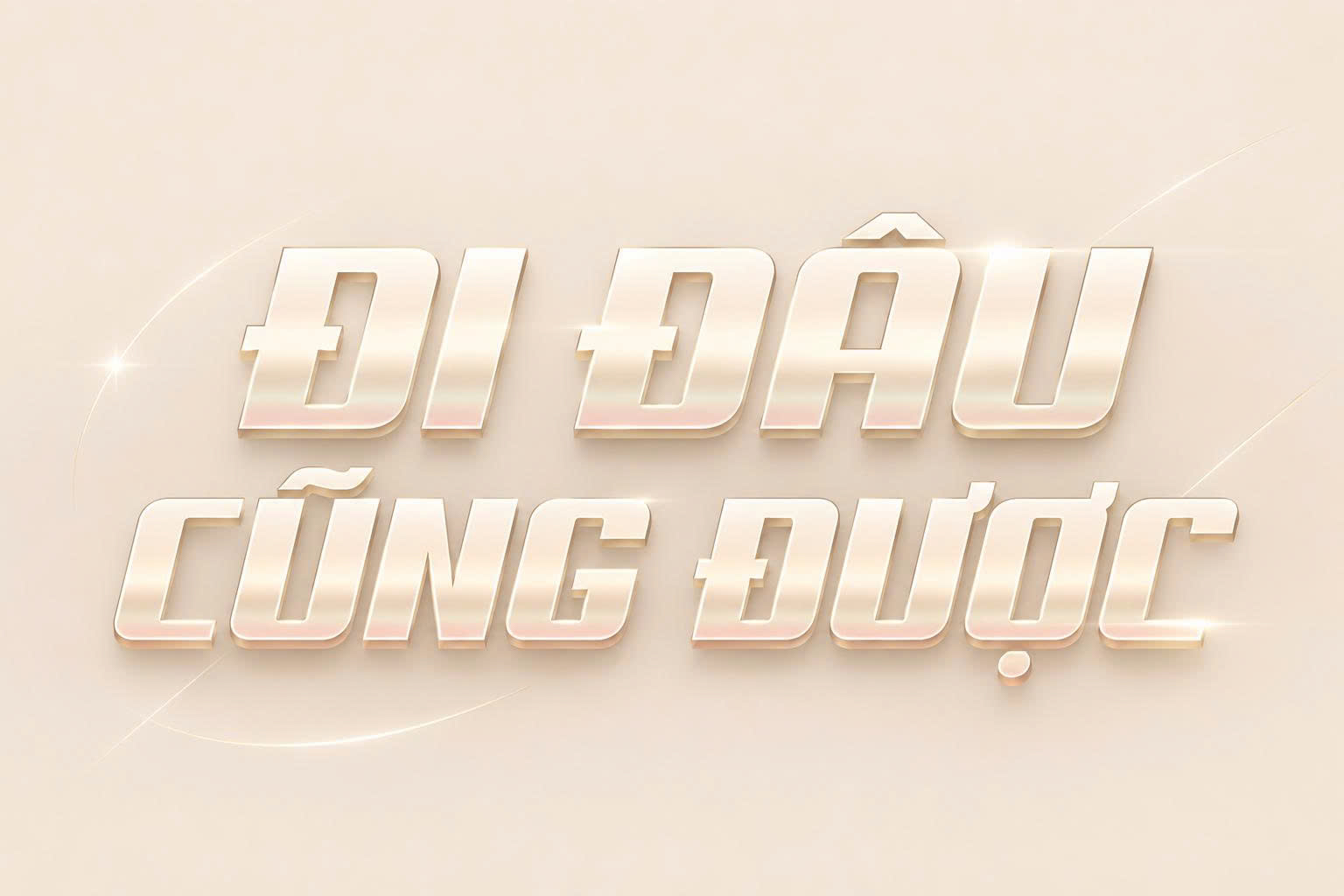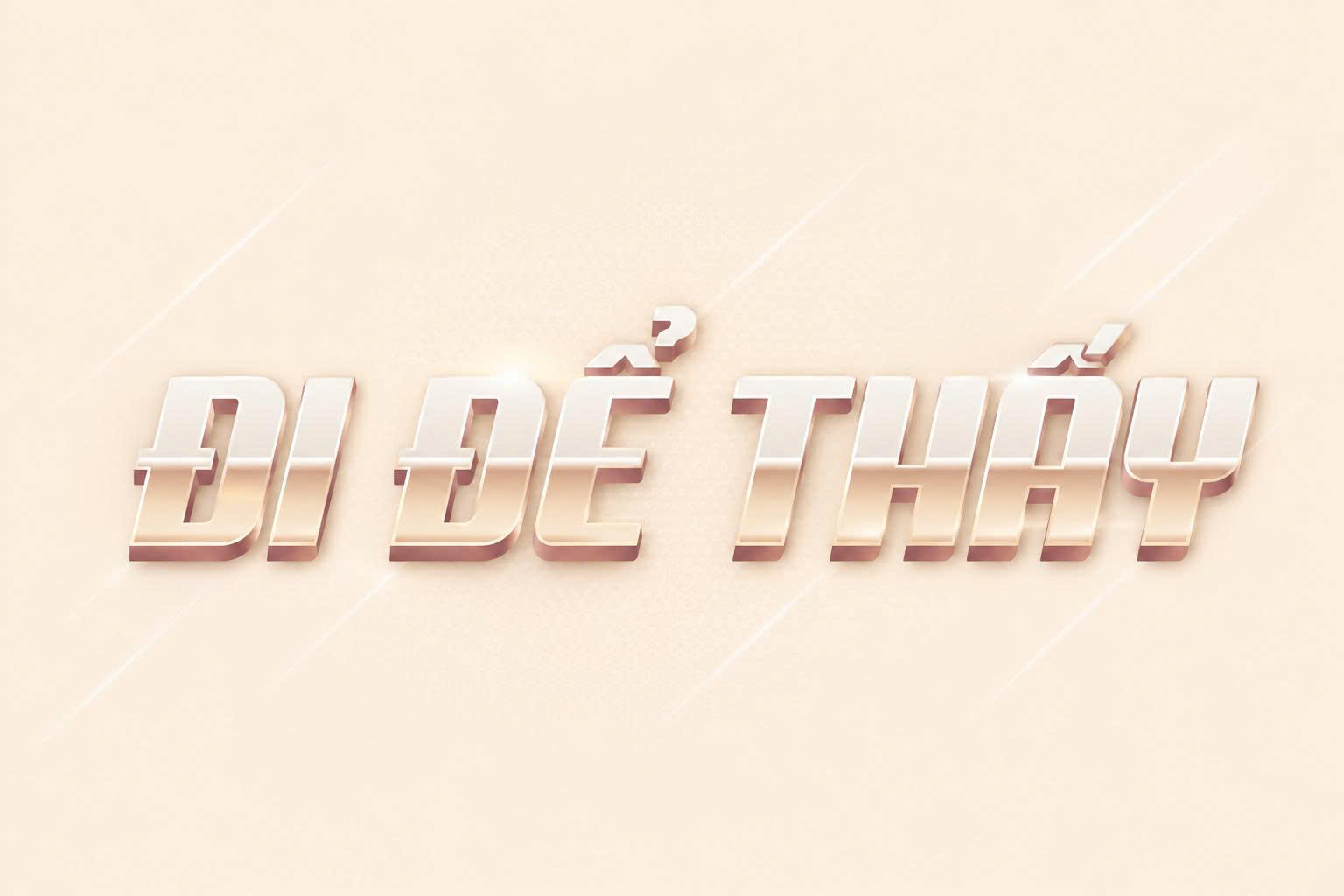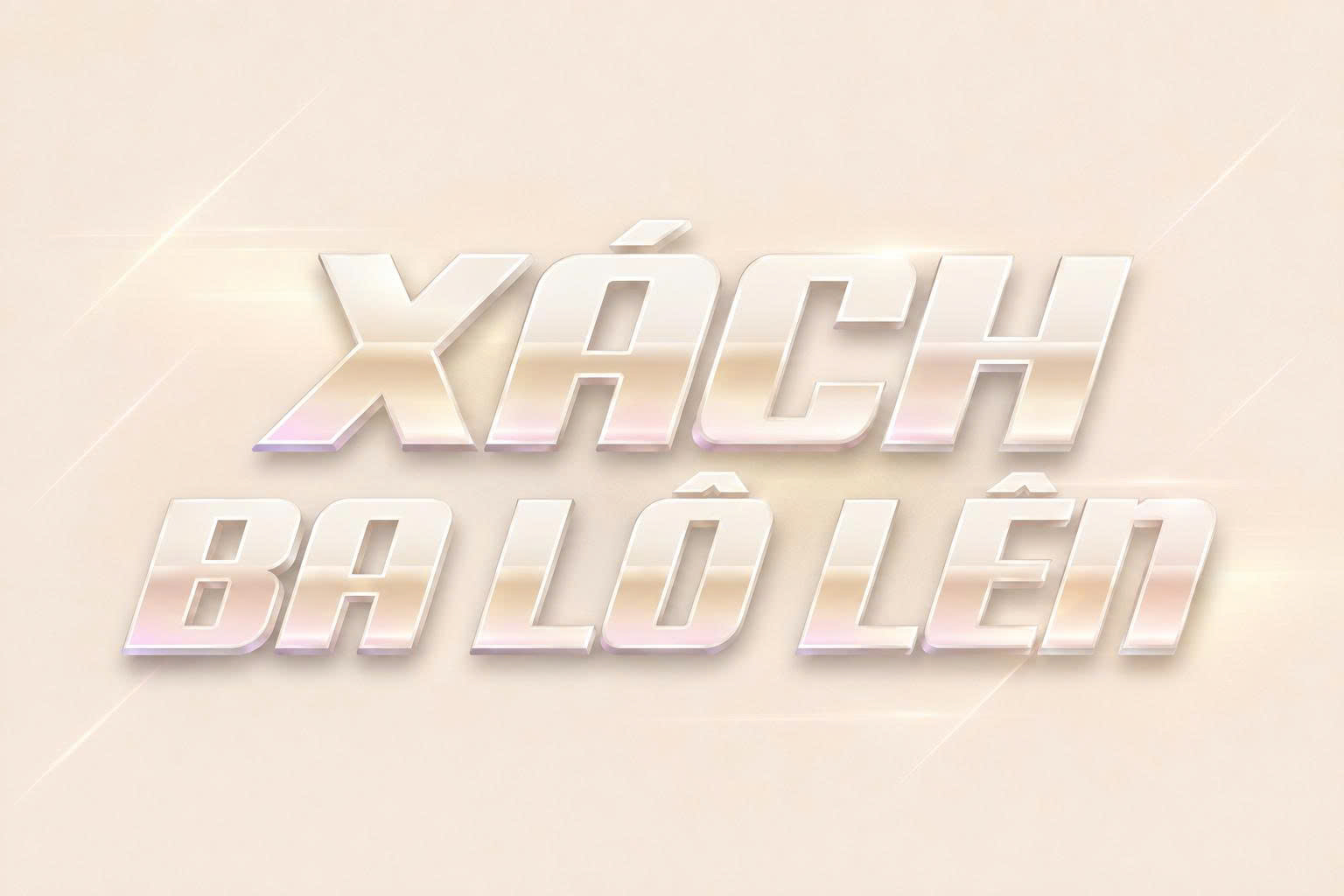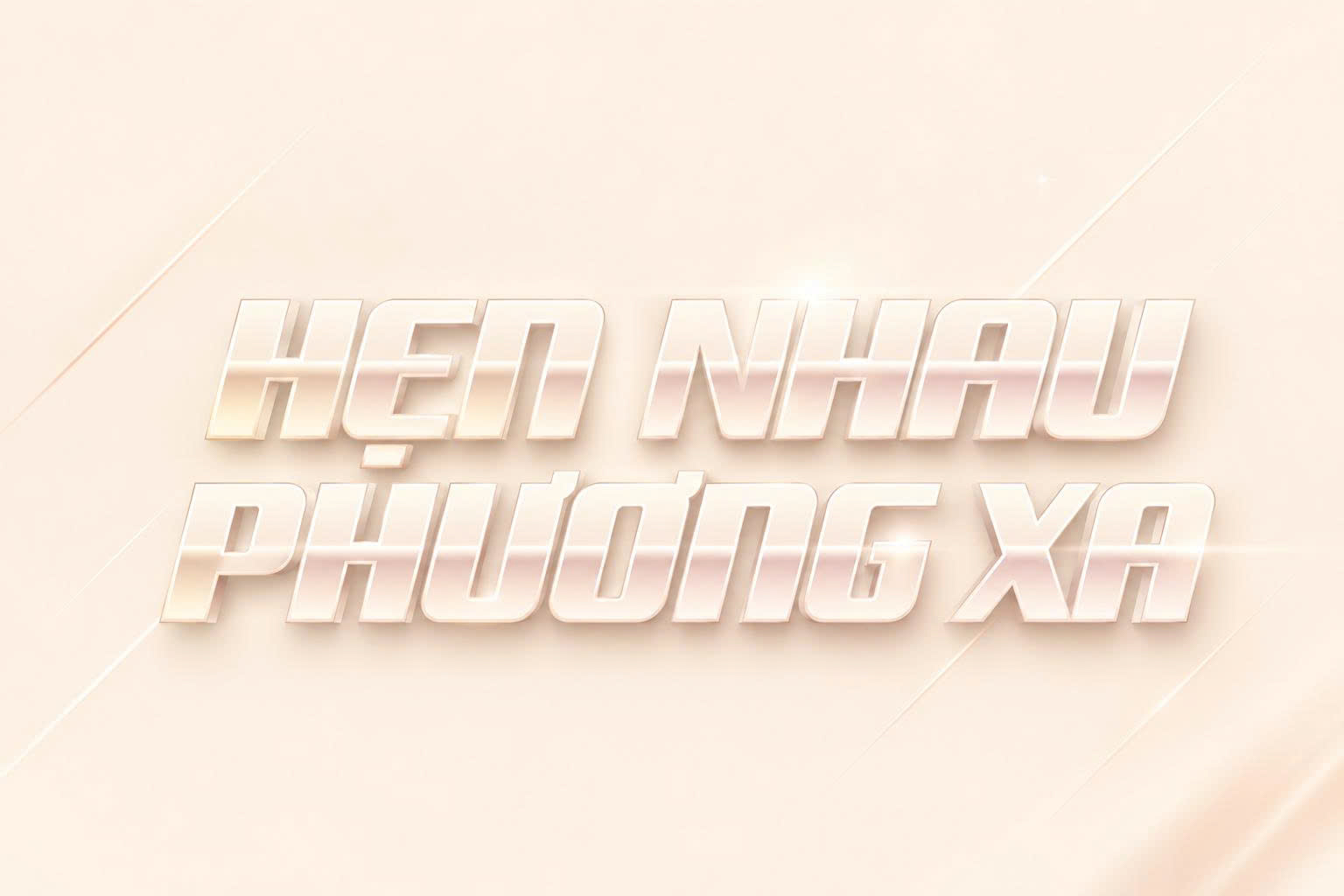
Font Aero Việt hóa là bộ phông chữ mang phong cách Futuristic (viễn tưởng) và Techno mạnh mẽ, nổi bật với những đường nét bo tròn mềm mại nhưng lại vô cùng dứt khoát. Với cấu trúc chữ mang hơi hướng khí động học, Aero là lựa chọn lý tưởng cho các thiết kế logo công nghệ, poster phim hành động hoặc bao bì sản phẩm điện tử. Doozypack.vn chia sẻ link tải phông chữ này chuẩn, giúp bạn sở hữu một bộ font hiện đại, không lỗi dấu để hiện thực hóa các ý tưởng thiết kế đầy tính sáng tạo.
Đặc điểm thiết kế của font Aero Việt hóa
Aero không chỉ là một phông chữ hiện đại thông thường, nó mang trong mình tinh thần của sự tốc độ, đổi mới và phong cách công nghiệp đương đại.
Phong cách khí động học và hiện đại
Đặc trưng lớn nhất của font Aero Việt hóa là cấu trúc chữ mở rộng với các góc bo tròn tinh tế, tạo cảm giác như những đường nét của các phương tiện siêu tốc hay các thiết bị công nghệ cao. Thiết kế này mang lại sự cân bằng giữa tính thẩm mỹ và công năng, giúp tiêu đề của bạn trông cực kỳ “high-tech” và lôi cuốn người xem ngay từ cái nhìn đầu tiên.
Khả năng hiển thị ấn tượng cho các tiêu đề lớn
Dòng font Aero được tối ưu hóa cho các tiêu đề (Heading) và các khối văn bản ngắn. Nhờ độ dày nét đồng đều và khoảng trống trong chữ được tính toán kỹ lưỡng, Aero duy trì được độ rõ nét đáng kinh ngạc. Khi được Việt hóa tại Doozypack.vn, hệ thống dấu tiếng Việt được đặt ở vị trí vô cùng tinh tế, đảm bảo không phá vỡ cấu trúc hình học chuẩn xác của font gốc.
Vì sao nên kết hợp font Aero và font Ethnocentric tiếng Việt?
Trong thiết kế phong cách Sci-fi (viễn tưởng), các designer thường có xu hướng kết hợp nhiều bộ font cùng chủ đề để tạo sự đa dạng. Bên cạnh Aero, việc sử dụng font Ethnocentric tiếng Việt là một gợi ý tuyệt vời. Cả hai bộ font này đều chia sẻ chung tư duy hình học và phong cách tương lai, giúp bộ nhận diện thương hiệu của bạn trở nên đồng nhất và mạnh mẽ hơn.
Việc tải font Ethnocentric Việt hóa cùng với Aero sẽ giúp bạn có thêm nhiều lựa chọn cho các cấp độ thông tin khác nhau trên bao bì sản phẩm, từ tên thương hiệu đến các thông số kỹ thuật cần sự minh bạch và hiện đại.
- Khoảng cách chữ (Tracking): Do cấu trúc chữ Aero hơi rộng bản, bạn nên điều chỉnh khoảng cách giữa các ký tự thủ công để tránh việc văn bản trông quá rời rạc trên bao bì thực tế.